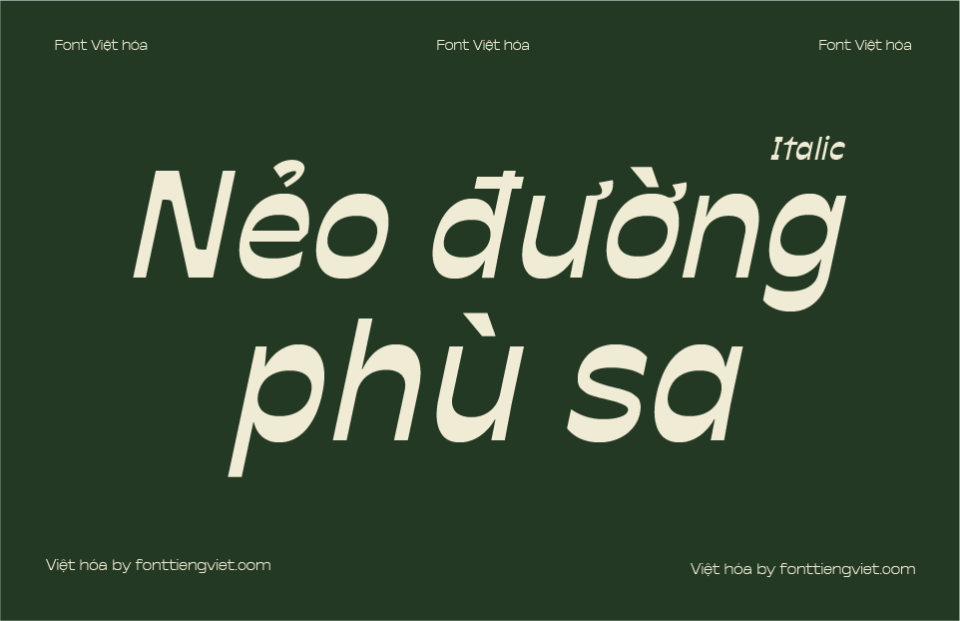
1FTV VIP Antipol Medium Italic Font Việt hóa
Tải Ngay 1FTV VIP Antipol Medium Italic Font Việt hóa – Đỉnh Cao Thiết Kế Hiện Đại
Giới thiệu về bộ 1FTV VIP Antipol Medium Italic Font Việt hóa
Trong thế giới đồ họa hiện đại, việc lựa chọn một bộ Font Miễn Phí chất lượng không chỉ giúp sản phẩm trở nên chuyên nghiệp mà còn tạo dấu ấn riêng biệt cho người thiết kế. Một trong những cái tên đang nhận được sự quan tâm lớn từ cộng đồng sáng tạo tại Việt Nam chính là 1FTV VIP Antipol Medium Italic Font Việt hóa. Đây là một phông chữ thuộc phong cách sans-serif hiện đại, mang trong mình vẻ đẹp của sự tối giản nhưng không kém phần mạnh mẽ. Với biến thể Italic (nghiêng) đặc trưng, bộ font này tạo ra cảm giác chuyển động linh hoạt và đầy tinh tế cho các tiêu đề hoặc các đoạn văn cần sự nhấn mạnh đặc biệt.
Đặc điểm thiết kế của 1FTV VIP Antipol Medium Italic Font Việt hóa
Dòng font Antipol vốn nổi tiếng với cấu trúc hình học chuẩn mực, các đường nét được tính toán kỹ lưỡng để đảm bảo độ cân bằng thị giác tuyệt đối. Ở phiên bản Medium Italic, độ dày của nét chữ nằm ở mức trung bình, giúp nó có khả năng hiển thị tốt trên cả nền tảng kỹ thuật số lẫn các sản phẩm in ấn như poster, bìa sách hay tạp chí học đường. Việc 1FTV VIP Antipol Medium Italic Font Việt hóa hoàn thiện bộ dấu tiếng Việt giúp các nhà thiết kế không còn phải lo lắng về lỗi hiển thị ký tự, đảm bảo tính thẩm mỹ đồng nhất cho toàn bộ văn bản. Điều này cực kỳ quan trọng đối với các bạn học sinh, sinh viên khi trình bày báo cáo hoặc thiết kế Slide thuyết trình chuyên nghiệp.
Tại sao nên sử dụng 1FTV VIP Antipol Medium Italic Font Việt hóa trong thiết kế?
Lý do đầu tiên khiến 1FTV VIP Antipol Medium Italic Font Việt hóa trở thành lựa chọn hàng đầu chính là sự đa năng. Bạn có thể sử dụng nó cho các biểu ngữ quảng cáo, nhận diện thương hiệu hoặc đơn giản là tạo ra những tấm thiệp chúc mừng đầy phong cách. Sự kết hợp giữa độ nghiêng tinh tế và các góc bo tròn nhẹ nhàng tạo nên một cảm giác thân thiện nhưng vẫn giữ được sự nghiêm túc cần thiết. Ngoài ra, phông chữ này còn mang lại sự rõ ràng trong việc đọc, giúp người xem dễ dàng tiếp nhận thông tin ngay cả khi được trình bày ở kích thước nhỏ.
Ứng dụng thực tế trong môi trường giáo dục
Trong môi trường học đường, việc sử dụng các font chữ mới mẻ như 1FTV VIP Antipol sẽ kích thích sự sáng tạo của học sinh. Giáo viên có thể dùng phông chữ này để thiết kế các bảng tin lớp học, sơ đồ tư duy hoặc các tài liệu học tập sinh động. Nhờ được Việt hóa kỹ lưỡng, mọi từ ngữ trong tiếng Việt đều được thể hiện một cách trơn tru, sắc nét. 1FTV VIP Antipol Medium Italic Font Việt hóa thực sự là một công cụ hỗ trợ đắc lực để biến những trang giấy trắng khô khan thành những tác phẩm nghệ thuật truyền cảm hứng cho người học.
Kết luận về giá trị của phông chữ Việt hóa